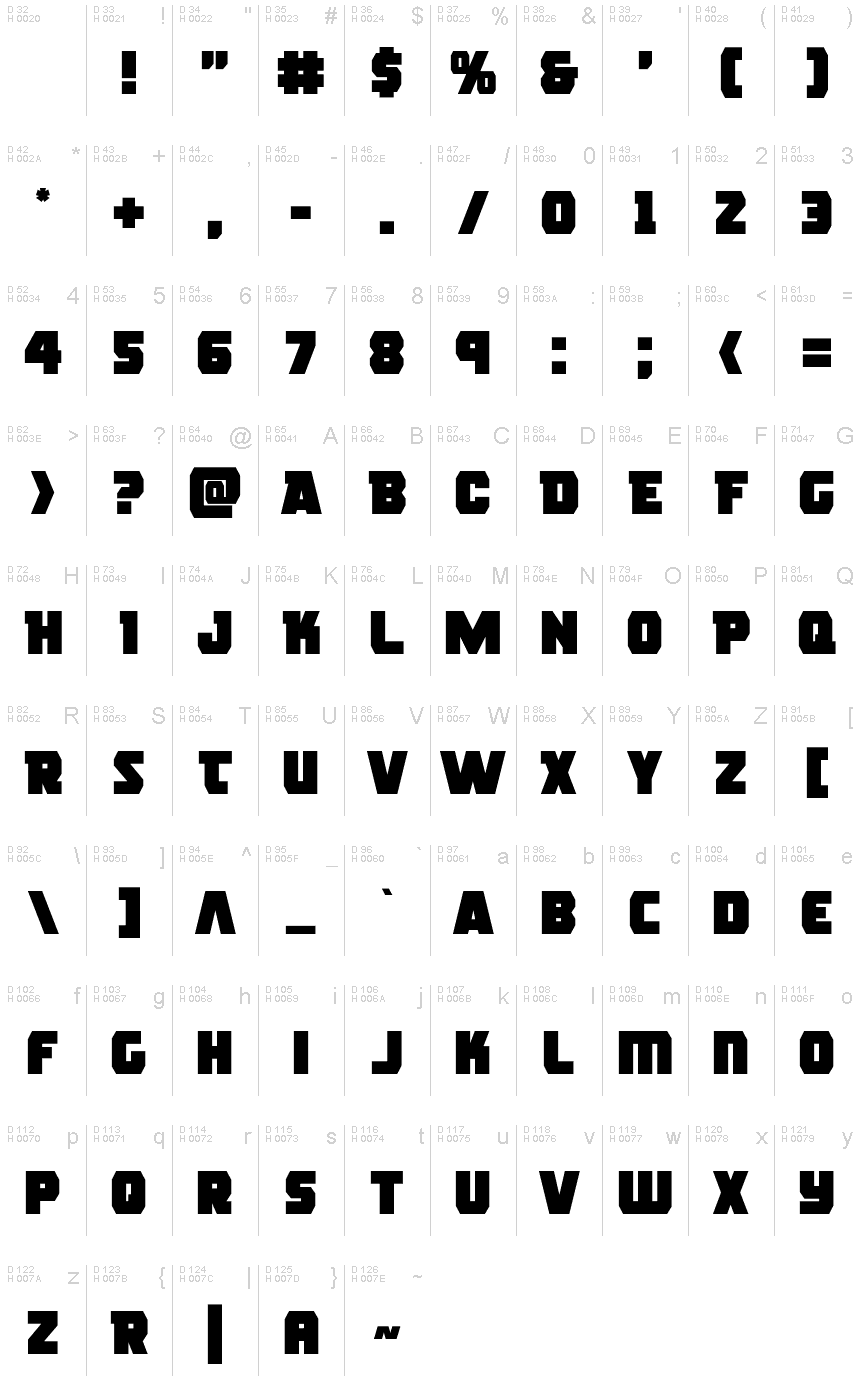
Rogue Hero
Rogue Hero od Iconian Fonts to darmowy krój typu display w stylu old-school, nawiązujący do surowej estetyki vintage sportowego liternictwa. Litery są szerokie, masywne i ostro cięte, z kwadratowymi narożnikami, głębokimi wcięciami oraz grubymi pionowymi kreskami, które nadają alfabetowi mocny, akademicki rytm.
Idealnie pasuje do brandingu sportowego, plakatów drużyn, opakowań gier w stylu retro, grafik na wydarzenia szkolne oraz odważnego merchandise'u, gdzie darmowy font z taką szatniową energią jest strzałem w dziesiątkę. Ponieważ wielkie litery są zwarte i wyraziste, Rogue Hero świetnie sprawdza się w krótkich nagłówkach, tytułach, nazwiskach na koszulkach sportowych czy monogramach, które wymagają charakternego, ikonicznego wyglądu.
Wersja 2 to całkowicie nowa odsłona kroju.